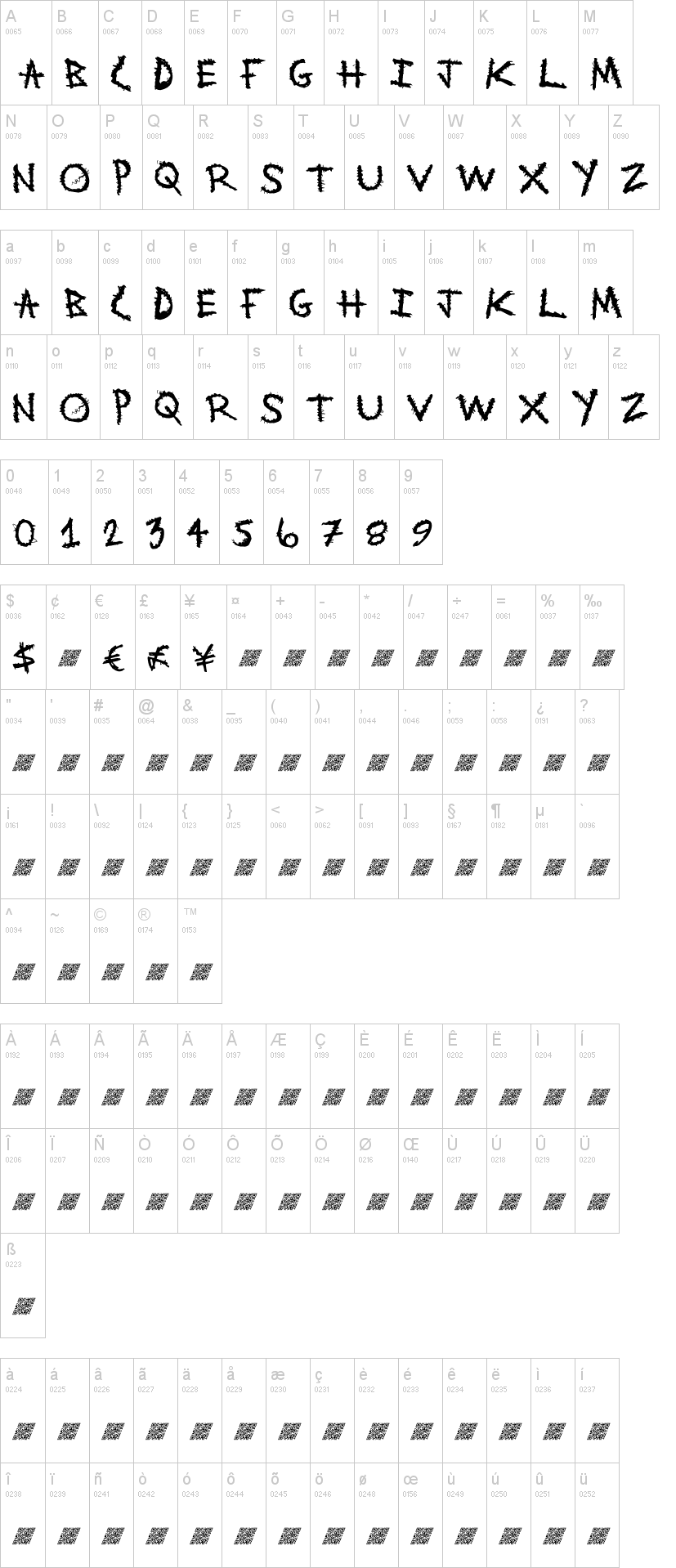
Metal Witch 是一种非常独特的字体,其设计灵感来自于重金属音乐、摩托车和黑暗魔法等元素。它的字形有着锋利、刚硬、有力的特点,与其灵感来源相呼应,给人一种强烈的视觉冲击感。Metal Witch 在设计上注重细节和纹理,每个字母都包含了很多细节元素,如锈迹、划痕、凹陷等,这些元素使其看起来更加生动和真实。 这种字体适合用于一些比较另类、独立的设计项目,如重金属音乐海报、魔幻小说封面、摩托车俱乐部标志等,可以为这些项目增加一份独特的个性和气质。同时,由于其字形比较刚硬,可能不太适合一些正式、商业性质的设计,如传统品牌标志等。内容介绍
Metal Witch是一款非常不错的手写艺术字体,具有很好的视觉感,适合于文化类的宣传设计、商业类品牌的广告和产品包装设计以及个性化文字排版等较多场景。